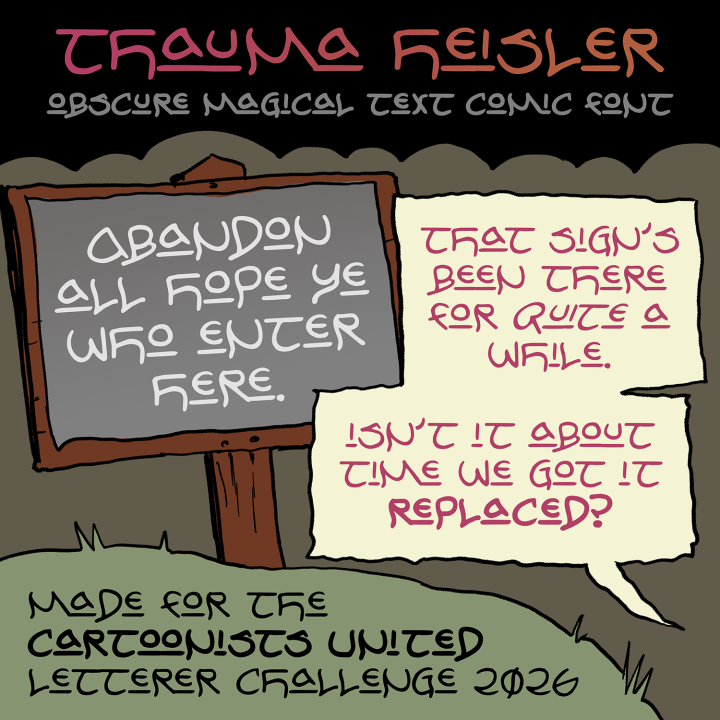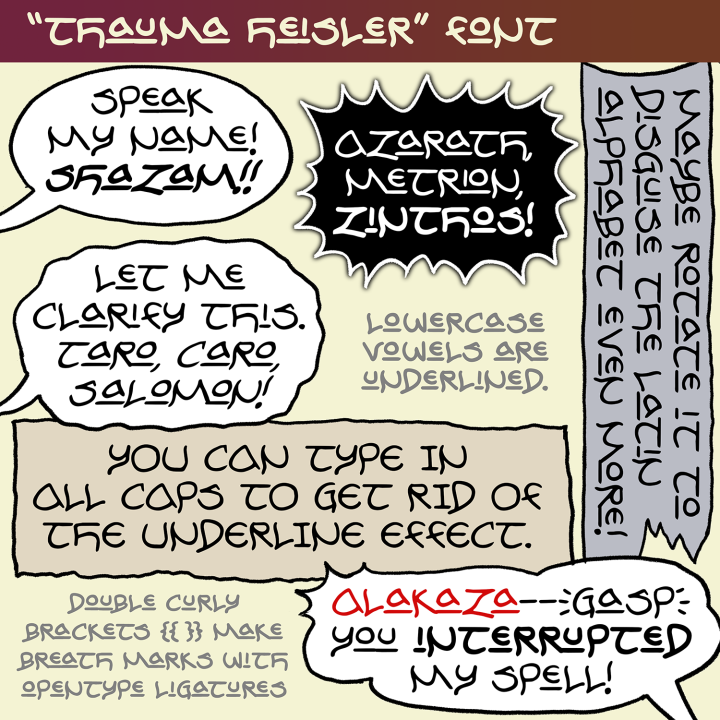
造型奇特、古色古香的Thauma Heisler奇幻字体素材,它借鉴了安色尔体的一些元素(特别是 Todd Klein 对古代安色尔字体的一些诠释),但更主要的灵感来源是 Mike Heisler 为电影《麦克斯》中的 Mr. Gone 设计的字体。
共有四种常规字体样式:常规体、斜体、粗体和粗斜体。斜体的字距调整不太理想,所有元音字母都有不带下划线的全尺寸版本,即大写形式(字母 I 还带有横线,符合漫画惯例)。除此之外,唯一独特的功能是呼吸符号,通过输入双花括号({{, }})来实现。